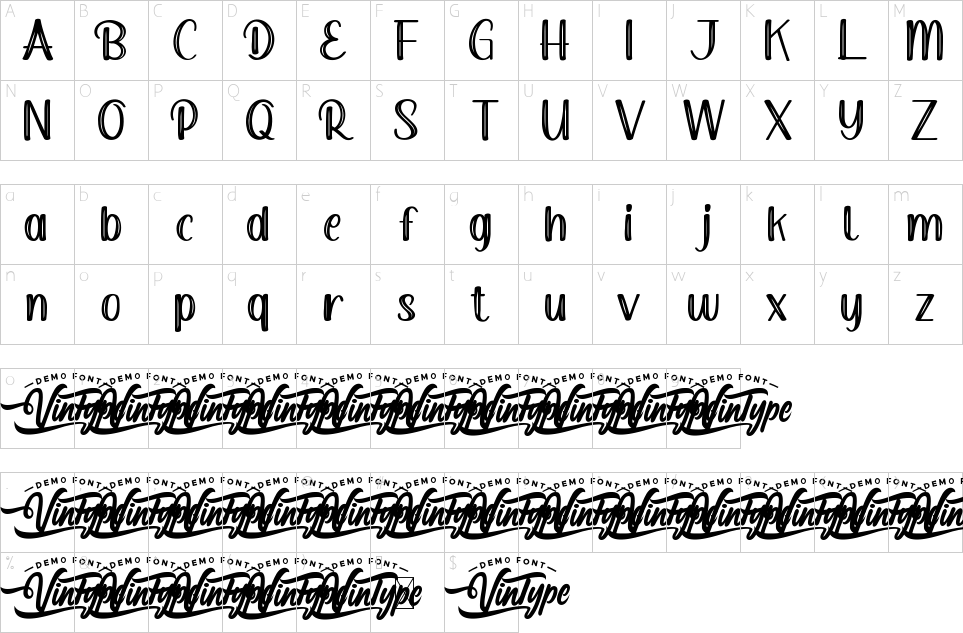
Aster Daisy Font – Download Grátis
Aster Daisy é uma fonte de graça que captura o encanto das flores em seu design. Seus traços delicados e delicados remetem à linda aster, com um toque de frescura e delicadeza, ideal para criações que exalam naturalidade. Esta fonte foi desenhada por vintype e já foi baixada 5.296 vezes. Não perca a oportunidade de adicionar um toque especial a suas criações com Aster Daisy, um design que transmite beleza e serenidade. Não há nada como a textura suave e a leveza das letras de uma boa fonte de graça para dar um toque de vida a qualquer projeto. Seja para assinatura, logotipo ou texto do site, Aster Daisy oferece uma maneira elegante de trazer um ar descontraído à sua identidade visual.